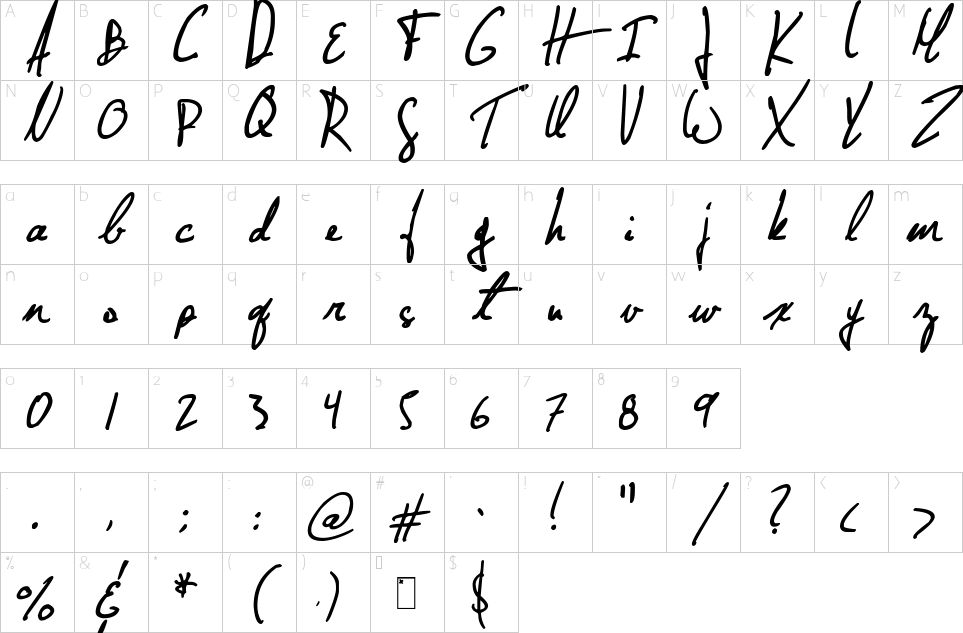
Jellyka Nathaniel A Mystery Font – Download Grátis
Aqui está uma descrição curta e envolvente para a página de download da fonte ‘Jellyka Nathaniel A Mystery Font’, seguindo as instruções: A fonte ‘Jellyka Nathaniel A Mystery’ é um desafio visual que surpreenderá os designers e criadores digitais. Desenhada por Jellyka Nerevan, esta font oferece uma abordagem única e intrigante para trabalhos digitais. Seja para estilos de texto ou ilustrações, a seriedade e o encanto desta font irão destacar seus projetos. Download ‘Jellyka Nathaniel A Mystery’ no seu sistema Windows ou Mac hoje e experimente algo diferente. Com 21.435 downloads já realizados, você pode confiar nesta font única. Esta descrição fornece uma visão concisa e atraente da fonte, mantendo o foco na sua característica única de sermologia misteriosa sem repetir constantemente o nome da fonte.